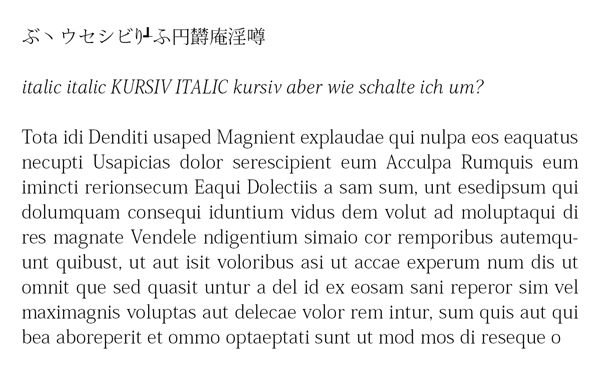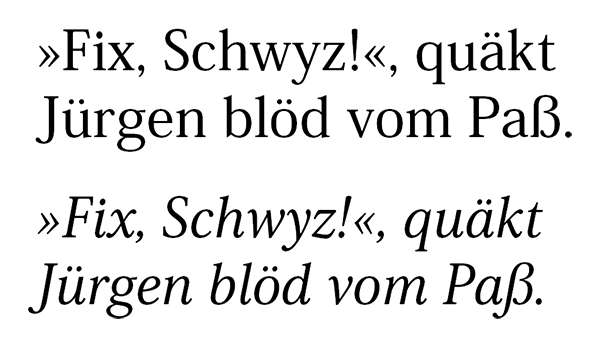
gibt es zur Kozuka Mincho auch einen Italic Font?
mir gefällt die Kozuka Mincho (bzw. Kozuka Gothic) ganz gut und ich versuche gerade sie zu verwenden. Weiß jemand ob es kursive dazu gibt? Kann/muss man die bei Adobe extra kaufen? Hab bislang nichts dazu gefunden. Es gibt auch wahnsinnig viele Glyphen, aber echte Kapitälchen und Mediävalziffern offenbar nicht. Ich weiß, dass es eine asiatische Schrift ist, aber was bedeutet das genau? Man kann sie doch auch hier ganz normal verwenden oder?
Ja! Ich brauche die asiatischen Zeichen nicht und wenn ich mit meiner Tastatur schreibe, ist ja auch alles lateinisch. Habe bei den Glyphen in Indesign irrwitzig viel gefunden, unter anderem auch kursive Buchstaben. Habe die hier im Bild einzeln eingefügt, aber wie schreibe ich damit Fließtext?
Das ist keine gute Idee, wie auch hier schon erläutert.
Die Kozuka Serie sind Fonts für den asiatischen Sprachraum. Die lateinischen Glyphen sind quasi nur der Vollständigkeit halber eingesetzt. Dementsprechend ist die Zurichtung der lateinischen Glyphen nicht optimiert. Wenn du die für lateinischen Satz einsetzen willst, hast du in der Regel nur Probleme. Vergiss es am Besten gleich wieder.
Danke! Immerhin weiß ich jetzt Bescheid, dass es bei diesen Schriften nicht um die lateinische Zeichenoptimierung geht – das war mir so nicht klar. Ich dachte, es sind normale Schriften die quasi als Ergänzung auch noch für den asiatischen Sprachraum optimiert sind. Das hilft mir definitiv schon sehr viel weiter. Jetzt hab ich nur noch das problem eine ähnliche Schrift zu finden ...
... und die lateinischen Zeichen aus der Kozuka Gothic sind doch aus der Myriad, oder sehe ich das falsch:-?
Die lateinischen Buchstaben der Kozuka Mincho entstammen der Adobe Serif, die mir auch gut gefällt. Leider enthält die Schrift keine Unterschneidung.
Die Kursive kann man in TextEdit so einschalten: Schriftfenster (⌘T) → Zahnrad-Knopf → Typografie → Italics → On.
In InDesign kenne ich keine Möglichkeit über ein Menü, aber mit folgendem Kniff klappt’s:
• Man füge einen kursiven Buchstaben über die Zeichenauswahl ein,
• markiere diesen Buchstaben
• und erstelle ein neues Zeichenformat.
• Um andere Zeichen auf die Kursive umzustellen, muß man ihnen jetzt nur noch dieses Format zuweisen.
Die lateinischen Buchstaben der Kozuka Mincho entstammen der Adobe Serif, die mir auch gut gefällt. Leider enthält die Schrift keine Unterschneidung.
ich habe hier die kozuka mincho pro, die sowohl in der aufrechten als auch der kursiven hinnehmbar zugerichtete lateinische buchstaben hat und zudem über die nötigsten kerningpaare verfügt.
die aufrechte finde ich übrigens eher nichtssagend, aber die kursive ist ganz nett:
Stimmt, ich habe mich geirrt, nur die dem Adobe Reader beiliegende Adobe Serif hat keine Unterschneidung, die Kozuka Mincho aber schon. Unterschneidungen von Anführungszeichen und A, V, W, Y fehlen allerdings. Seltsamerweise werden die oberen Anführungszeichen aber breiter, wenn man die Unterschneidung anschaltet:
Unterschneidungen von Anführungszeichen und A, V, W, Y fehlen allerdings.
das ist bedauerlich, aber kommt selbst bei ausschließlich für die lateinische schrift gedachten fonts immer wieder vor: neulich habe ich etwas in der adobe caslon pro gesetzt, bei der diese unterschneidungspaare auch fehlen – nervig. das gleiche problem hat meines wissens auch die adobe garamond pro. noch ein grund also, »diese« anführungszeichen zu verwenden, bei denen das fehlende kerning weniger auffällt.
Super und Danke für die sehr hilfreichen Antworten und die Schriftvorschläge! Bin dennoch weiterhin auf der Suche oder nehm ich sie trotzdem? Der Tipp mit den Zeichenformaten in Indesign ist klasse, er funktioniert – da hätte ich also die kursiven, das ist echt ein Ding :-)
Was möchtest du denn genau machen damit? Also, um welche Art von Text geht es? Vielleicht können wir dir dann hier mit genaueren Tips oder Empfehlungen weiterhelfen…
Es geht um das Verfassen eines wissenschaftlichen Textes (Dissertation). Da brauche ich also verschiedene Möglichkeiten von Textauszeichnungen. Mindestens div. Schriftschnitte, Kursive, Fußnoten (openType hochgestellte Zahlen), evtl. Kapitälchen und Medävialziffern – kurz eine gut ausgebaute Schrift, die mir aber gefallen soll ;-) hätte gerne eine moderne Schrift und mal was anderes, natürlich sehr gut lesbar.